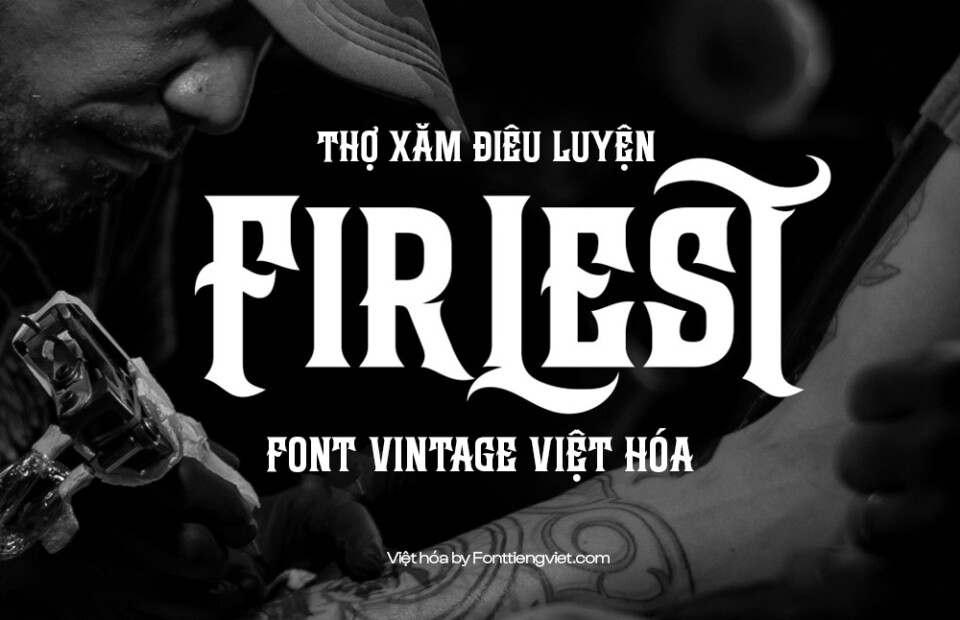
Font Việt hóa 1FTV VIP Firlest – Font Việt hóa vintage – Sự lựa chọn hoàn hảo cho thiết kế hoài cổ
Trong thế giới sáng tạo, việc lựa chọn một bộ Font Chữ phù hợp đóng vai trò quyết định đến linh hồn của tác phẩm. Font Việt hóa 1FTV VIP Firlest – Font Việt hóa vintage là một bộ font đặc biệt, mang đậm hơi thở cổ điển và sự sang trọng tinh tế. Được thiết kế dành riêng cho những ai yêu thích vẻ đẹp xưa cũ nhưng vẫn muốn giữ nét chuyên nghiệp, bộ font này đã nhanh chóng trở thành công cụ đắc lực cho cộng đồng thiết kế tại Việt Nam nhờ khả năng hỗ trợ tiếng Việt hoàn chỉnh và chuẩn xác nhất.
Đặc điểm nổi bật của Font Việt hóa 1FTV VIP Firlest – Font Việt hóa vintage
Phong cách thiết kế độc bản
Bộ font này sở hữu những đường nét uốn lượn mềm mại, kết hợp cùng các chi tiết thanh đậm được tinh chỉnh kỹ lưỡng. Điều này giúp Font Việt hóa 1FTV VIP Firlest – Font Việt hóa vintage tạo nên một cảm giác ấm cúng, gần gũi nhưng không kém phần quý phái. Nó cực kỳ phù hợp cho các dự án thiết kế bìa sách, thiệp mời đám cưới, hoặc các ấn phẩm truyền thông mang tính nghệ thuật cao.
Tối ưu hóa cho người dùng Việt
Một ưu điểm lớn của phiên bản này là hệ thống dấu tiếng Việt được thiết kế cân đối, không bị lỗi hiển thị hay chồng chéo. Bạn có thể tự tin sử dụng trên các phần mềm đồ họa phổ biến mà không lo ngại về vấn đề kỹ thuật.
Ứng dụng thực tế của font chữ trong giáo dục và sáng tạo
Các bạn học sinh và giáo viên có thể dùng bộ font này để trang trí báo tường, làm slide bài giảng hoặc thiết kế các chứng nhận khen thưởng độc đáo. Sự trang nhã của nó giúp nội dung trở nên thu hút và dễ đi vào lòng người hơn. Nếu bạn đang tìm kiếm một giải pháp Typography chất lượng, hãy trải nghiệm ngay Font Miễn Phí, Font Việt Hóa, Font Việt hóa 1FTV VIP Firlest – Font Việt hóa vintage để nâng tầm giá trị cho mọi sản phẩm thiết kế của mình trong năm nay.